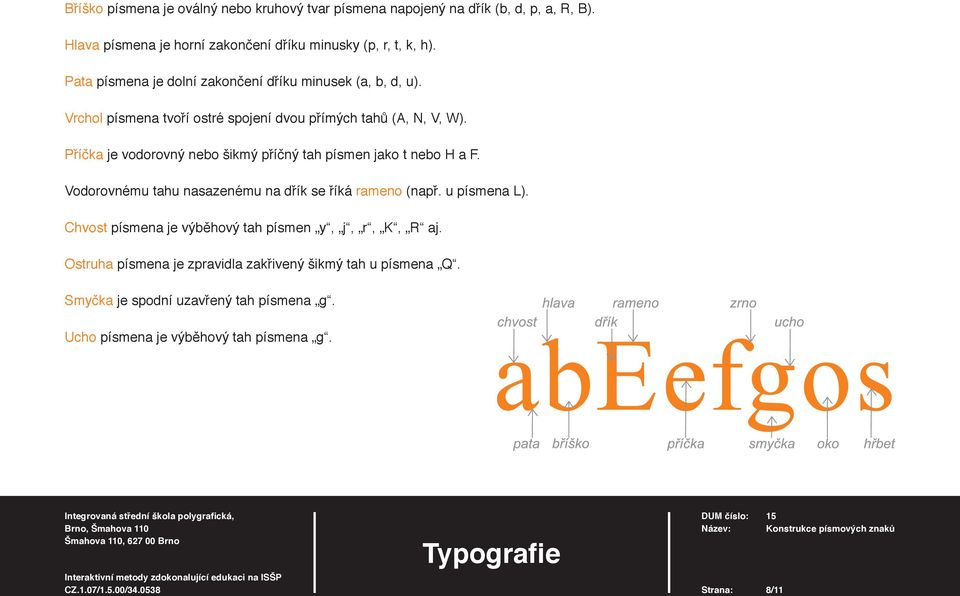
15. Konstrukce písmových znaků. Typografie
3 Se zpracováním textu je spojen pojem typografi e, pocházející z řeckých slov typos (úprava) a graphein (psát). Typografi i je možné chápat jako umění uspořádat text. Je důležitou složkou grafi ckého návrhu a měla by vždy směřovat ke dvěma hlavním cílům čitelnosti a vizuální poutavosti. Dobrá typografi e usnadňuje čtenáři vnímání textu; typografi cké zásady, které jsou založeny na zkušenostech získávaných po několik století, proto nejsou samoúčelné a mají význam i v současnosti. Většina písem obsahuje: písmena velké abecedy majuskule neboli verzálky, písmena malé abecedy minuskule neboli minusky, akcentované znaky, číslice, interpunkční znaménka, matematické operátory a další často používané znaky. Počet znaků potřebných pro sazbu je větší než rozsah klávesnice. Speciální znaky písem vkládáme do textu pomocí mapy znaků. Většina písem obsahuje: VERZÁLKY minusky ěščřžýáíéúů ,. ; : - & * Rodina písma je skupina řezů odvozených z jednoho typu písma, které zajišťuje jednotný vzhled sazby. Úplná písmová rodina obsahuje: základní písmo a jeho vyznačovací řezy kurzíva, tučný řez, tučná kurzíva, popř. polotučný řez, polotučná kurzíva, kapitálky. Rodina písma základní písmo kurzíva tučný řez tučná kurzíva KAPITÁLKY Strana: 3/11
4 Konstrukce písma Při tvorbě písma se vychází z písmové osnovy. V tištěném textu ji neuvidíme. Je to pomyslná soustava vodorovných linií, tzv. dotažnic, které jsou důležité při návrhu písma. Typografi e Á akcentová dotažnice horní dotažnice střední výška písma základní dotažnice účaří dolní dotažnice Základní dotažnice (účaří písma) je linie, na které sedí jednotlivá písmena. Střední výška písma (výška minusky x) je vymezena vzdáleností střední dotažnice od účaří. Oblá písmena (o, p, c, atd.) v minuskách i verzálkách mírně překračují účaří i střední nebo horní dotažnici. Říká se tomu přetah (pokud by nebyl, písmeno by působilo opticky menší). Horní dotahy jsou zpravidla svislé tahy minusek (b, d, f, h, k, l, t). Výška těchto tahů je vymezena vzdáleností účaří a horní dotažnice. Tato vzdálenost také u řady písem defi nuje výšku verzálek. Některá písma mají snížené verzálky. Strana: 4/11
5 Dolní dotahy jsou svislé tahy minusek (g, j, p, q, y). Výškově jsou defi novány vzdáleností účaří a dolní dotažnice. Pro umísťování verzálkových akcentů je určena akcentová dotažnice. Minuskové akcenty potřebují vlastní akcentovou dotažnici, která se ve většině případů kryje s horní dotažnicí. Proporcionální rozvržení písmové osnovy je u každého typu písma jiné a tím mu vtiskuje osobitý charakter. Čím je výška písma větší, tím menší jsou horní i dolní dotahy. Písmo větší střední výšky je lépe čitelné i v malých velikostech, protože se v tisku jeho tahy neslévají. Na dobré čitelnosti se podílí mnoho činitelů, které ovlivňují čtenáře. Snahou je, aby čtení neunavovalo a písmo i celková úprava působily esteticky, doplňovaly a zvýrazňovaly obsah tiskoviny. Strana: 5/11
6 Proporcionální a neproporcionální písma Čtverčík je rozměr čtverce daného velikostí kuželky v bodech. Do formátu čtverčíku vychází verzálka M. Jednotky získáme rozdělením čtverčíku na 18 jednotek. Každý písmový znak má přidělen jiný počet jednotek. Takové písmo nazýváme proporcionální a jsou to všechna typografi cká písma. U neproporcionálního písma je to jinak, řídí se podle nejšiřšího znaku a text psaný tímto písmem je nevyrovnaný. Čtverčík rozdělený na 18 jednotek Times proporcionální písmo Courier New neproporcionální písmo Proporcionální písmo Neproporcionální písmo Ukázka přidělení počtu jednotek Strana: 6/11
7 Kresba písmového znaku Obraz písmových znaků je vyjádřen hlavními a vedlejšími tahy, které tvoří kresebné prvky písmových znaků. Vzájemnou odlišitelnost písem ovlivňuje jejich kresba v základním obrysovém tvaru (skelet). Kontury znaků mimo jiné určují duktus, ovlivňující zabarvení potištěné plochy. Jedná se o výraznost kresby písma, vyjádřenou tloušťkou tahů znaků v poměru k jejich výšce. Tahy většiny písem mají proměnnou tloušťku. Písmové znaky 16 a 28 bodů duktus duktus Zesilování částí nebo celých tahů znaku, zvláště hlavních tahů a oblouků, se říká stínování. Stínování se svislou osou se nazývá statické, při dynamickém stínování je osa obvykle nakloněná doleva. Kromě stínování má na kontury znaků vliv i způsob zakončení tahů, přičemž časté je příčné zakončení v podobě serifů (patek). Nakloněná osa Svislá osa Dřík písmena hlavní svislý nebo šikmý tah. Hřbet hlavní oblý tah tvořící jeho páteř (S). Serify (nesprávně patky písma) ukončují tahy písmen. Různé druhy serifů ovlivňují čitelnost písma. Hlavní tah ukončený jiným kresebným způsobem než serifem se nazývá výběh (zakončení může mít např. tvar slzy nebo zrna). Náběh je propojení dříku se serifem nebo oblého tahu (bříška) s přímým tahem. Oko je uzavřený oválný tvar písmen o, g, Q, který není spojen s dříkem. Strana: 7/11
8 Bříško písmena je oválný nebo kruhový tvar písmena napojený na dřík (b, d, p, a, R, B). Hlava písmena je horní zakončení dříku minusky (p, r, t, k, h). Pata písmena je dolní zakončení dříku minusek (a, b, d, u). Vrchol písmena tvoří ostré spojení dvou přímých tahů (A, N, V, W). Příčka je vodorovný nebo šikmý příčný tah písmen jako t nebo H a F. Vodorovnému tahu nasazenému na dřík se říká rameno (např. u písmena L). Chvost písmena je výběhový tah písmen y, j, r, K, R aj. Ostruha písmena je zpravidla zakřivený šikmý tah u písmena Q. Smyčka je spodní uzavřený tah písmena g. Ucho písmena je výběhový tah písmena g. Strana: 8/11
9 Velikost textu v bodech Se zpracováním textu je spojen pojem typografie, pocházející z řeckých slov typos (úprava) a graphein (psát). Typografii je možné chápat jako umění uspořádat text. Je důležitou složkou grafického návrhu a měla by vždy směřovat ke dvěma hlavním cílům čitelnosti a vizuální poutavosti. Se zpracováním textu je spojen pojem typografie, pocházející z řeckých slov typos (úprava) a graphein (psát). Typografii je možné chápat jako umění uspořádat text. Je důležitou složkou grafického návrhu a měla by vždy směřovat ke dvěma hlavním cílům čitelnosti a vizuální poutavosti. Se zpracováním textu je spojen pojem typografie, pocházející z řeckých slov typos (úprava) a graphein (psát). Typografii je možné chápat jako umění uspořádat text. Je důležitou složkou grafického návrhu a měla by vždy směřovat ke dvěma hlavním cílům čitelnosti a vizuální poutavosti. Se zpracováním textu je spojen pojem typografie, pocházející z řeckých slov typos (úprava) a graphein (psát). Typografii je možné chápat jako umění uspořádat text. Je důležitou složkou grafického návrhu a měla by vždy směřovat ke dvěma hlavním cílům čitelnosti a vizuální poutavosti. Se zpracováním textu je spojen pojem typografie, pocházející z řeckých slov typos (úprava) a graphein (psát). Typografii je možné chápat jako umění uspořádat text. Je důležitou složkou grafického návrhu a měla by vždy směřovat ke dvěma hlavním cílům čitelnosti a vizuální poutavosti. Se zpracováním textu je spojen pojem typografie, pocházející z řeckých slov typos (úprava) a graphein (psát). Typografii je možné chápat jako umění uspořádat text. Je důležitou složkou grafického návrhu a měla by vždy směřovat ke dvěma hlavním cílům čitelnosti a vizuální poutavosti. Se zpracováním textu je spojen pojem typografie, pocházející z řeckých slov typos (úprava) a graphein (psát). Typografii je možné chápat jako umění uspořádat text. Je důležitou složkou grafického návrhu a měla by vždy směřovat ke dvěma hlavním cílům čitelnosti a vizuální poutavosti. Se zpracováním textu je spojen pojem typografie, pocházející z řeckých slov typos (úprava) a graphein (psát). Typografii je možné chápat jako umění uspořádat text. Je důležitou složkou grafického návrhu a měla by vždy směřovat ke dvěma hlavním cílům čitelnosti a vizuální poutavosti. 6 bodů nonpareille 7 bodů kolonel 8 bodů petit 9 bodů borgis 10 bodů garmond 11 bodů breviář 12 bodů cicero 14 bodů střední Strana: 9/11
10 Kontrolní otázky: 1. Co obsahují písmové sady? 2. Zakresli a popiš písmovou osnovu. 3. Vysvětli rozdíl mezi proporcionálním a neproporcionálním písmem. 4. Co je to duktus, dřík a serif? Strana: 10/11